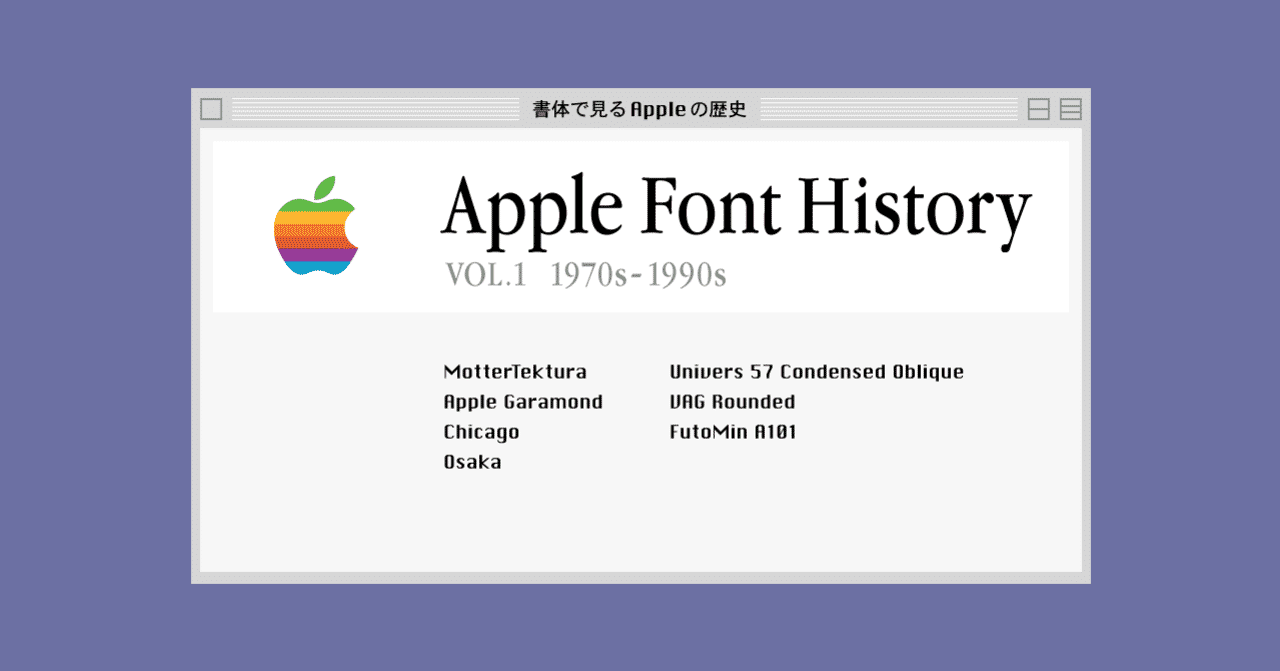
Apple ロゴ フォント. Apple製品だけで利用可能な アップルロゴ絵文字(りんごマーク)をご紹介します。この絵文字には UF8FF という文字コードが与えられており、MacやiPhone、iPadなどのApple製品で利用できますが、WindowsパソコンやAndroidでは となり何が書いてあるのか分からない文字となります。. 以下のフォントは、そのフォントがすでに使われている書類や、そのフォントが名前で指定されている App の中でだけ利用できます。 一部は、以前のバージョンの Mac オペレーティングシステムや Apple 製 App に組み込まれていた古いフォントです。. Apple製品のロゴのフォントはMyriad(ミリアド) そして昔懐かしのロゴフォント「Apple Garamond」はなぜかフリーダウンロード可能に。 弊社CEOが「うちのロゴは iPod みたいなフォントがいいなあ」と言ったとか言わないとかで、標題の件を調べたことがあります。.
WebDogにてApple製品のロゴのフォントはMyriad(ミリアド) というエントリーが上がっています。 エントリー名にある現在のアップル製品のロゴのフォントはMyriad Proだという結論に違和感を感じたので、改めて調べてみました。. Advertisement Apple社はiPhoneやiPod、iMacなどのロゴをひとつのフォントで統一しています。 使われているフォントは「Myriad」というフォントになっており、シンプルですっきりとしたデザイン. Appleロゴマーク・フォント違い いつもブログ入稿はiPhoneで 打ち込むのですが (↓iPhoneの画面) iPhoneには🍎のフォント文字が.
アップルがロゴに使ったフォントの変遷(Myriad, Apple Garammond, MotterTektura など). 「apple computer」というタイポグラフィは、ライアン・スミス(Ryan Smith)によるデザイン。 フォントは「Motter Tektura」(by Otmar Motter in 1975)を使用し、1977年に発売された「Apple II」 より採用された。. MacやiPhone、iPadなどのApple製品でアップルロゴ(Appleマーク? コレ⇒ )を入力する方法です。MacやiPhone、iPadといったAppleの製品にはアップルのロゴの特殊文字(コレ⇒ )が用意.